1. 字体的阴阳线
笔划设计融入了书写的韵味,采用“阴阳”线的处理方法,讲究线条之美,使笔划挺拔有力,刚柔相济——这是方正字体高级设计师齐立在【字与字现场】的一句PPT。
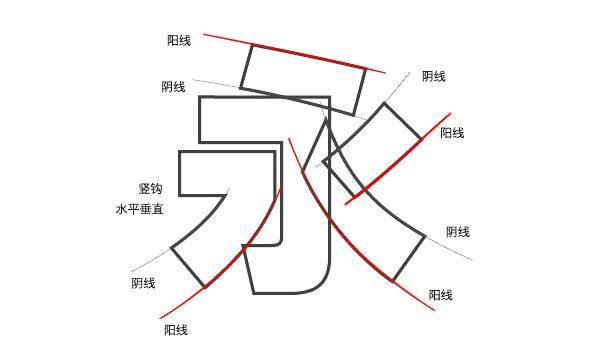
中国古代万物有阴阳,讲究阴阳美学,汉字亦是如此。所以了解字体笔划阴阳关系做字体,能使笔划看起来更加沉稳、刚柔、挺拔、美观。
咋一看好像很玄乎的说法,阴阳线。其实理解起来也很简单,字体有重量的,所以分粗细,单个笔画的2侧就是阴阳线。结合单个字体来看,字体每一笔画外围向阳(凸线的笔画比较容易懂,上图红色部分),即为阳线,内阴(凹线笔画上图红色对应的笔画)则为阴线。
所谓阴阳收缩法就是根据阴阳关系调整笔画的粗细关系与整个字体结构的处理方法。似乎有点难理解,我们看个例子。
2. 个例分析
1. 案例为DNF男枪的一个版本专题。枪战类的字体风格应该是有力度感,硬朗、男性、苍劲有力。依然是先找案例参考。
2. 选取一款非衬线字体做基础字体,线条可以稍粗,有力度感点的。
上面3种字体是常见的我们在游戏页面使用的字体,个人偏好造字工坊版黑常规体。
方正粗谭黑简体重心靠上,笔画显散,但是一款非常适合做变形的字体,特别是FPS等。
造字工坊劲黑常规体也是在游戏里常见到的流行字体,字体笔画较粗,重心很稳,但笔画调整起来稍显麻烦,不是所有的场合都使用。
造字工坊版黑常规体字是我在DNF中经常用的原型字体,字体笔画粗细得当,重心也会比其他字体稳,易于调整和变形。(造字工坊的字体结构和重心挺稳,易于变形,值得推荐。)
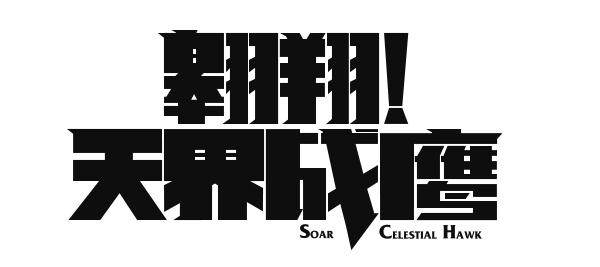
选择造字工坊版黑常规体之后,先是字体结构和重心调整(参见字体故事一),把原字体笔划按需要加粗,局部笔划调整,再添加衬线装饰(参见字体故事二),然后就有了如上的一个字体效果。这里尖角元素加的比较少。此篇主要讲阴阳线收缩法,下面就是本节的主要内容。
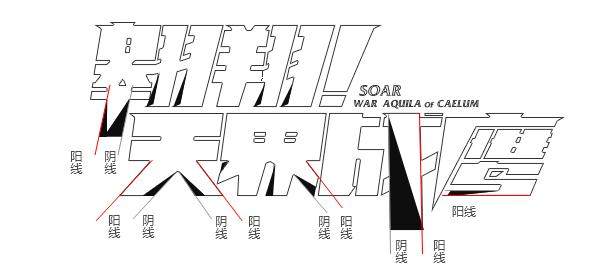
DNF男枪主题风格,在调整了结构重心,添加了少量衬线装饰后,个性还不够,需要进一步加强。结合男性身材倒三角的形状,对字体进一步个性处理。我们根据倒三角这样一个概念,把字体的水平重心上面的笔划保持不变,按阴阳线收缩调整下部分笔划,即把字体灰色线的笔划向红色线的笔画方向做倾斜处理(即阴线向阳线方向收缩),这样单个字体着地点小,字上身大,使笔画看起来成倒三角形。
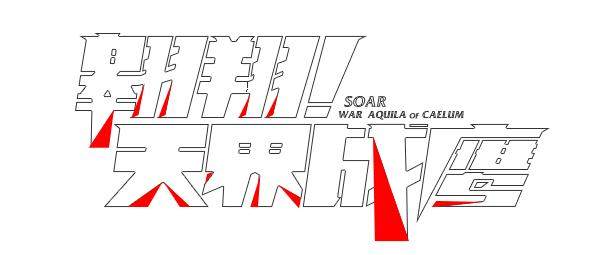
经过调整后的字体,个性就明显很多,也显得更有力度感,符合男枪版本的主题。看完可能有的同学还是不太理解这个概念。简单来说其实这个阴阳收缩法只是一个方法命名。核心就是如何调整粗细笔画2侧(阴面和阳面),使其看起来更显个性、彰显魅力、符合主题。
最后我们来看看,完整版的字体效果。
3. 类举分析
“创新世纪”是早前DNF版本的字体设计的其中一稿。创新世纪,想到的是新纪元,新的开始,用了比较力度感的方式,和线条。这一稿也是运用了阴阳线收缩的方法去处理。
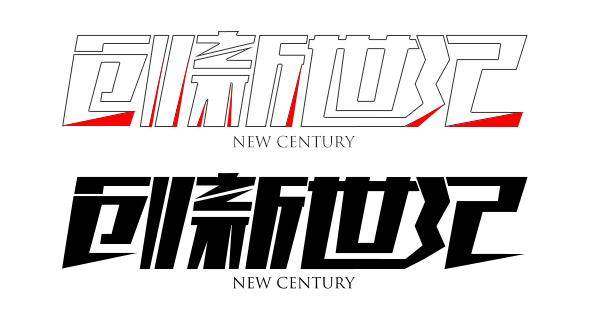
“海库”烧烤店logo的一版,烧烤要力度感、火力、野性。所以字根部分也是笔划缩进后处理的效果。
“偶像日记”是当初爱奇艺针对TFboys的做的一款类似花儿与少年的街头真人show节目。要青春时尚,年轻,有火力感方案。
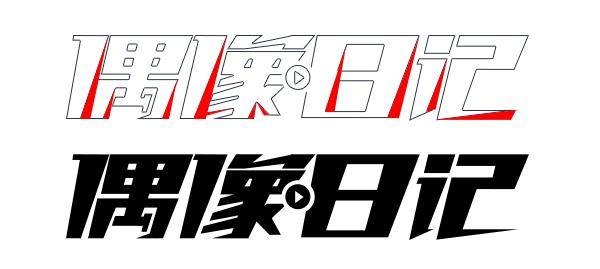
“燃尽一切”是疾风之刃一个版本的字体尝试,联想到疾风之刃是漫画风格的游戏,结合logo的形状和字体风格,做的一种方案。
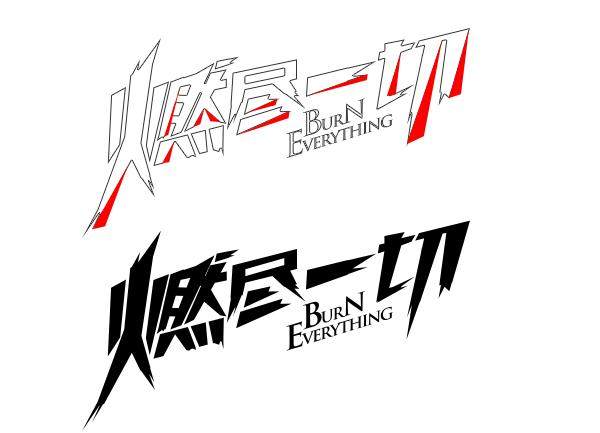
上一篇,衬线加强法只是列举了我个人做的一些例子,为了更有说服力,我也列举下大家网上看到,或者已有的成功案例。
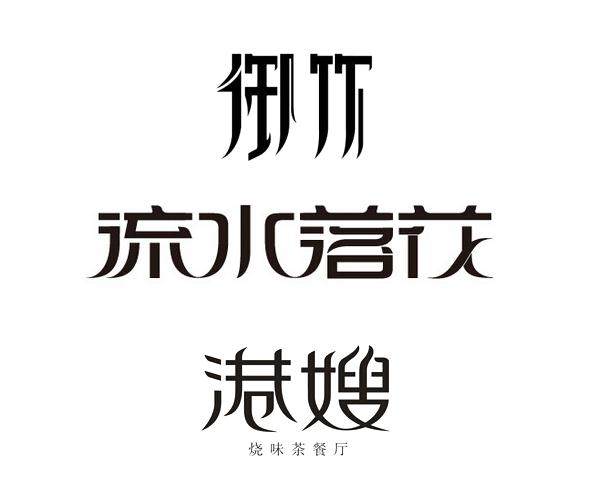
这几种字体都是阴阳线调整字根等位置处理的效果。当然也是调整了字体结构、重心,添加衬线等方法而成的。这里是阴阳线都是用了比较柔和的曲线收缩的,所以看起来很柔和、流动感很强,符合主题。